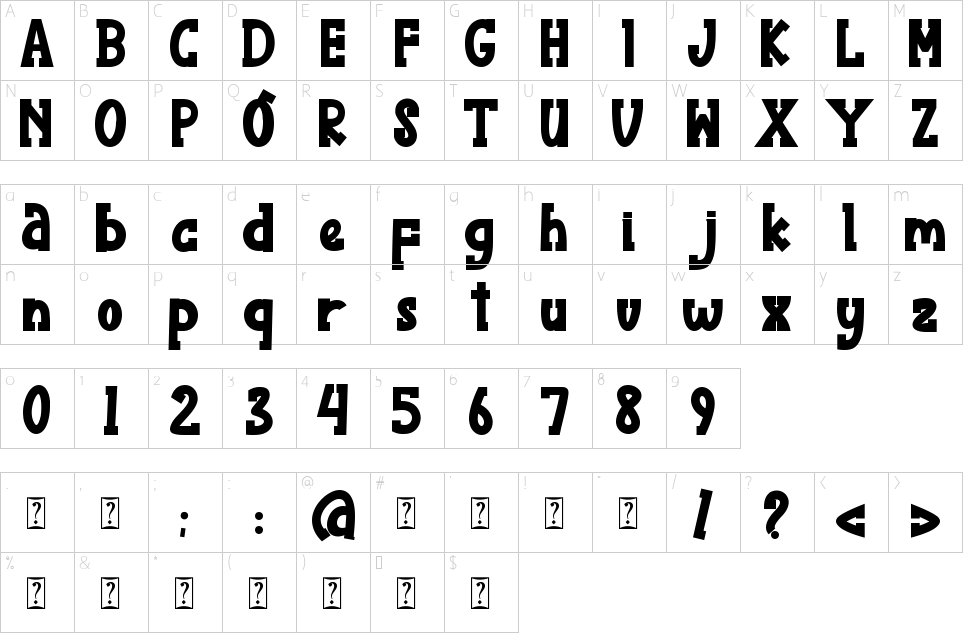
A Geralize é uma fonte que oferece um toque moderno e clean para agradar os designers gráficos. Ela foi criada pelo designer Yoga Letter e já foi baixada 881 vezes, evidenciando sua popularidade entre profissionais de design. Se você está procurando por uma fonte elegante que não exige muitos cuidados, Geralize é uma excelente escolha para seu trabalho. Com uma arquitetura de letras minimalista e fácil de ler, ela se adapta perfeitamente a um grande número de projetos gráficos digitais. Para aqueles buscando fontes gratuitas em alta qualidade, a Geralize é uma opção definitivamente a considerar.